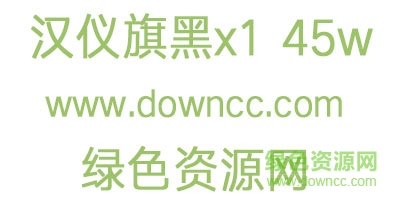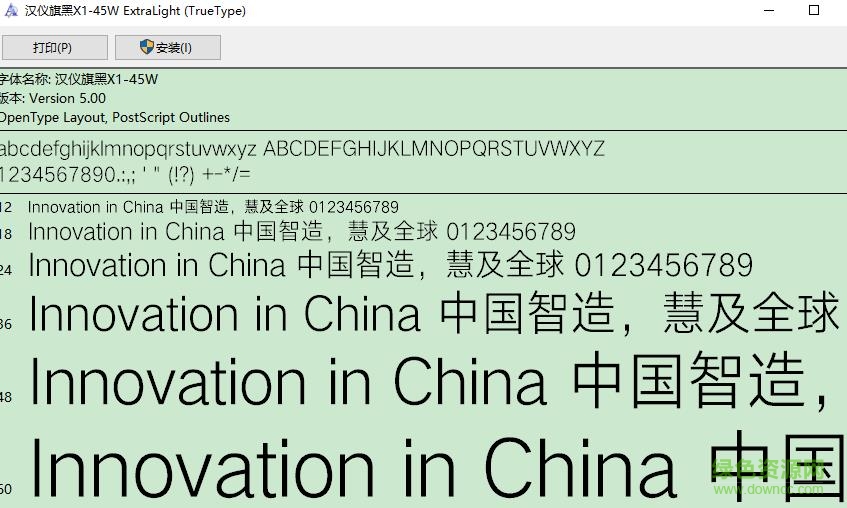
漢儀旗黑x1 45w是一款常用的簡(jiǎn)體字體,這款漢儀字體字形美觀,結(jié)構(gòu)端正大方,字體端莊典雅,應(yīng)用領(lǐng)域也非常的廣泛,歡迎大家來綠色資源網(wǎng)免費(fèi)下載使用!
漢儀旗黑是由三個(gè)系列字體(長、方、扁)組成的一個(gè)龐大而完整的家族字體,從最細(xì)的25到最粗的105,共計(jì)15個(gè)字重,是迄今為止國內(nèi)最大、最豐富的字重的家族字體,可以滿足企業(yè)多渠道,全方位的內(nèi)容設(shè)計(jì)以及定制化需求,實(shí)現(xiàn)企業(yè)品牌形象在各渠道的統(tǒng)一呈現(xiàn)。